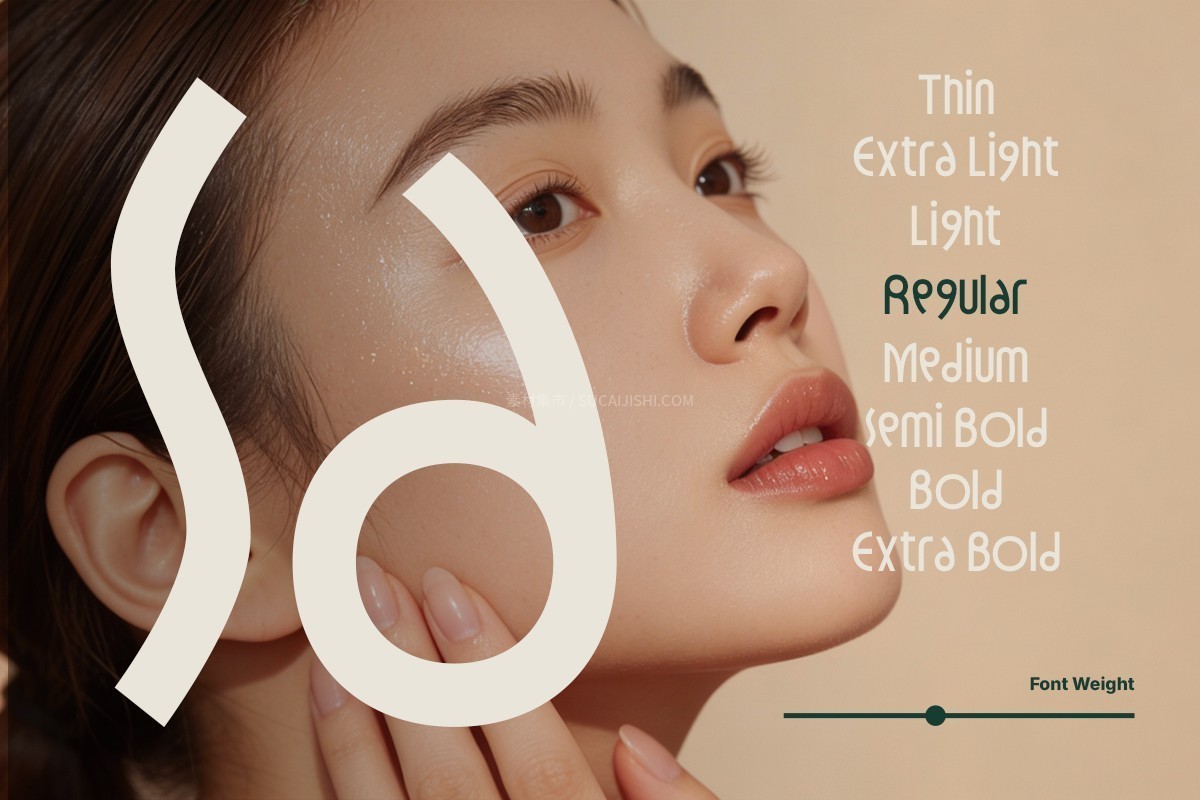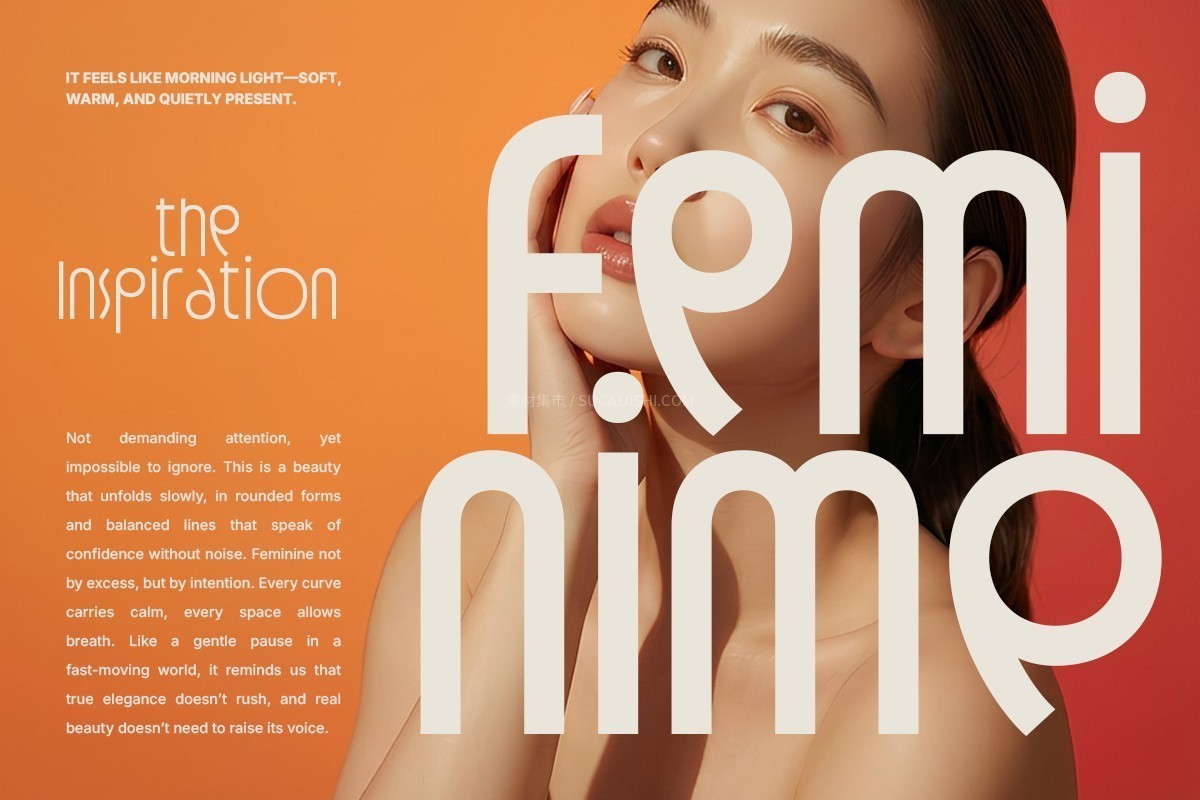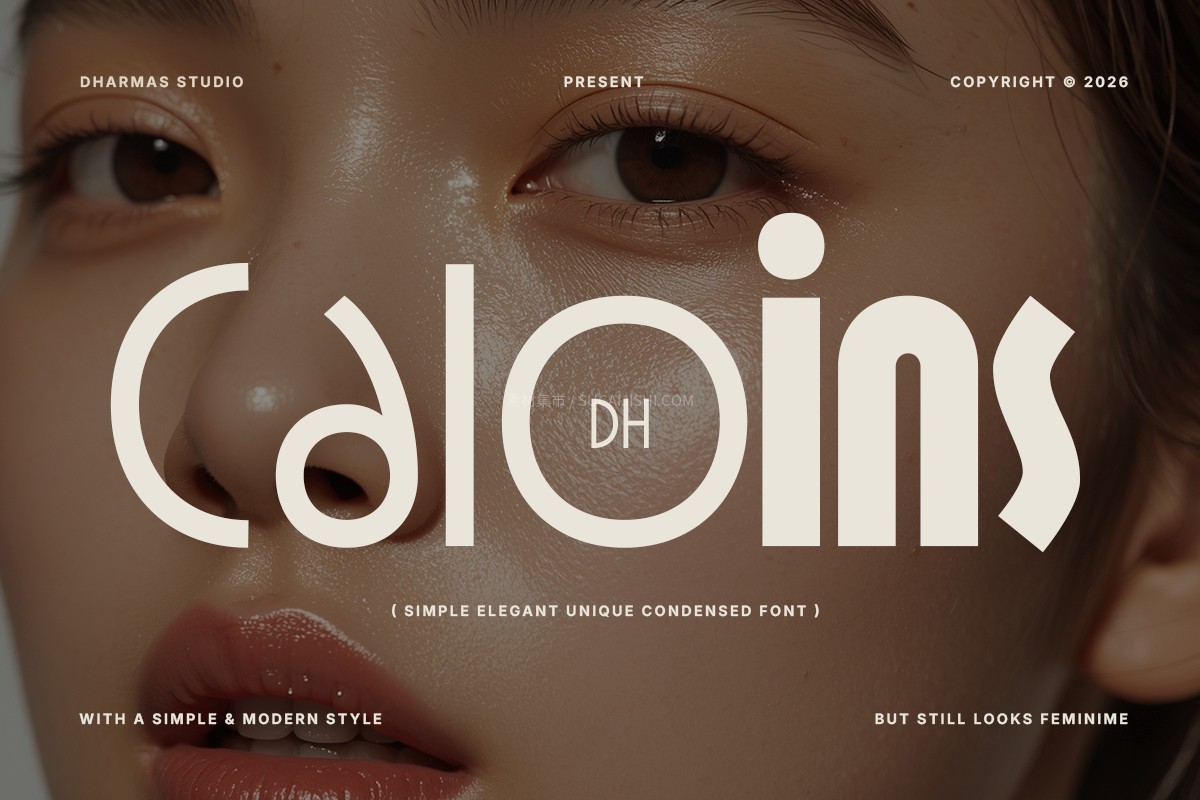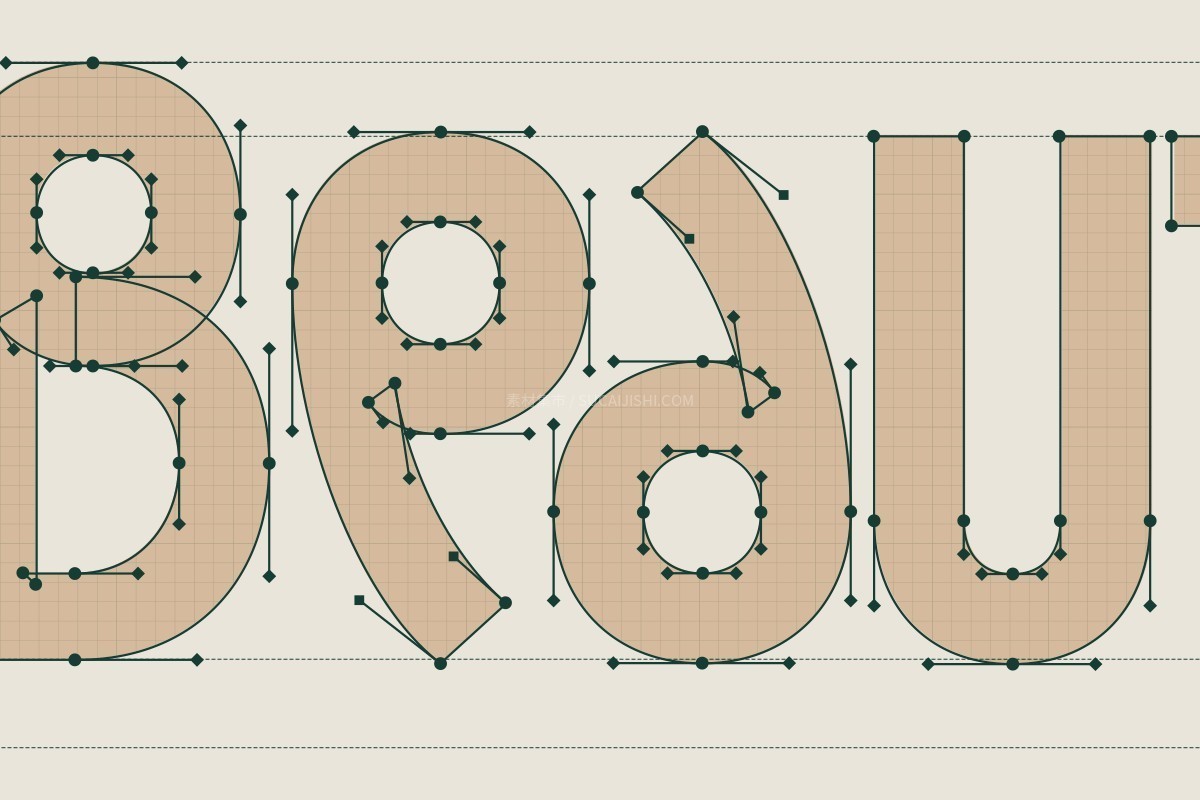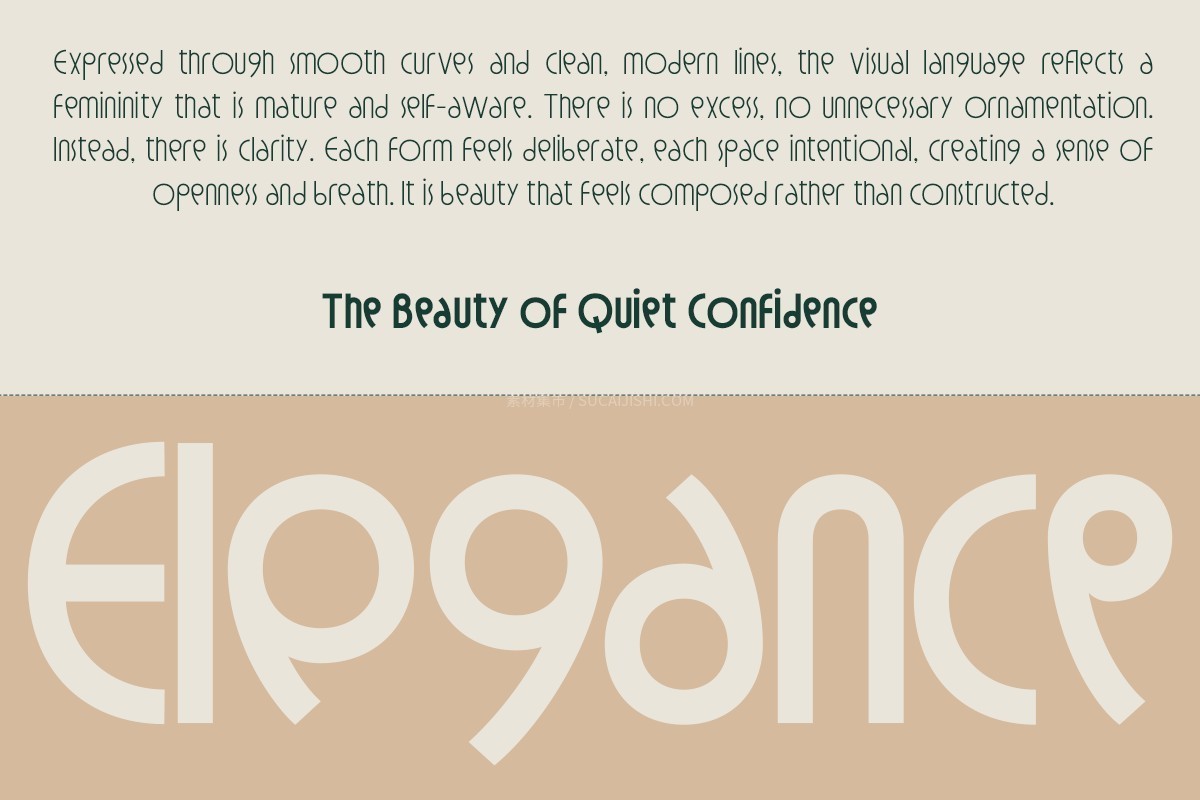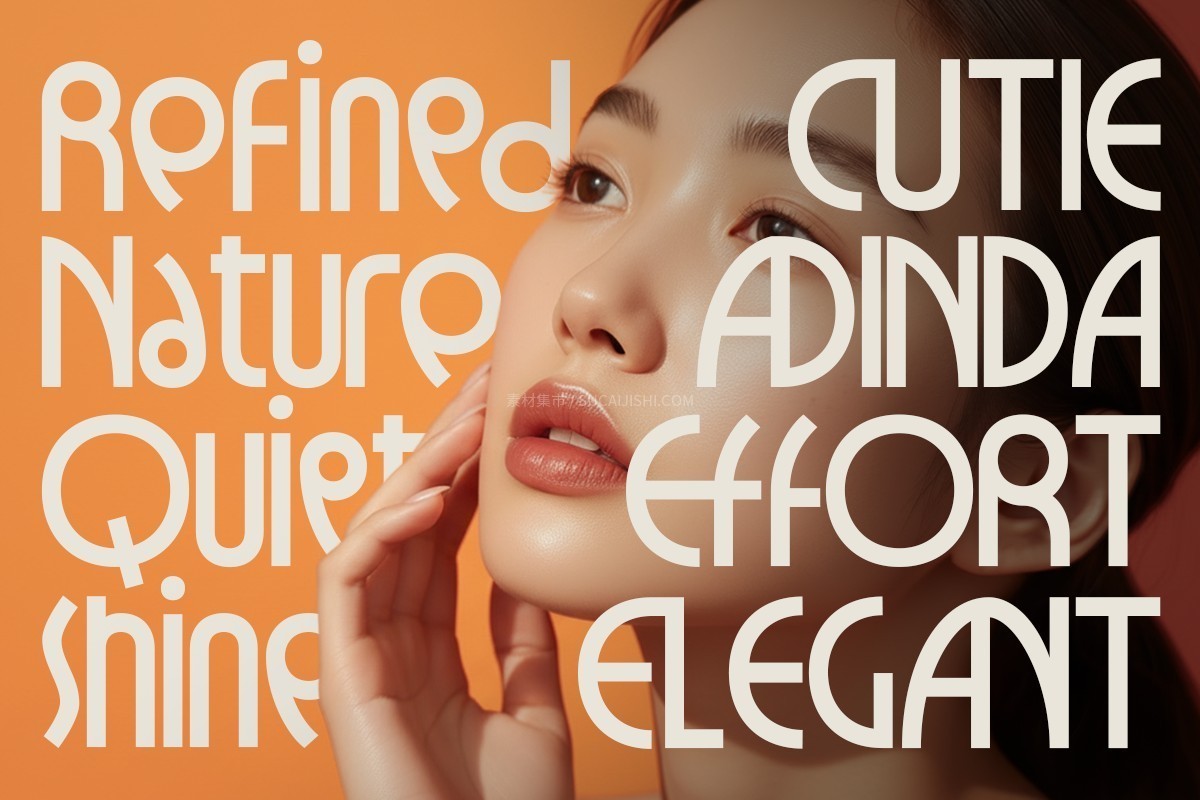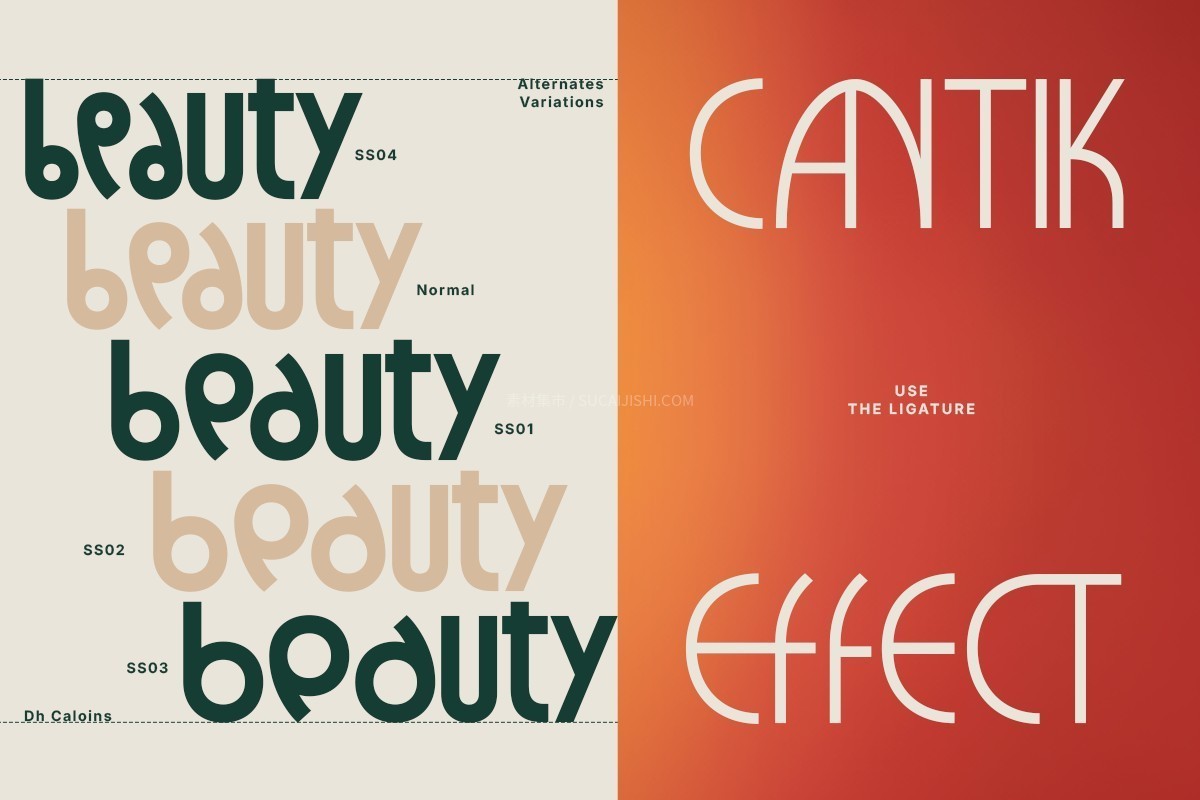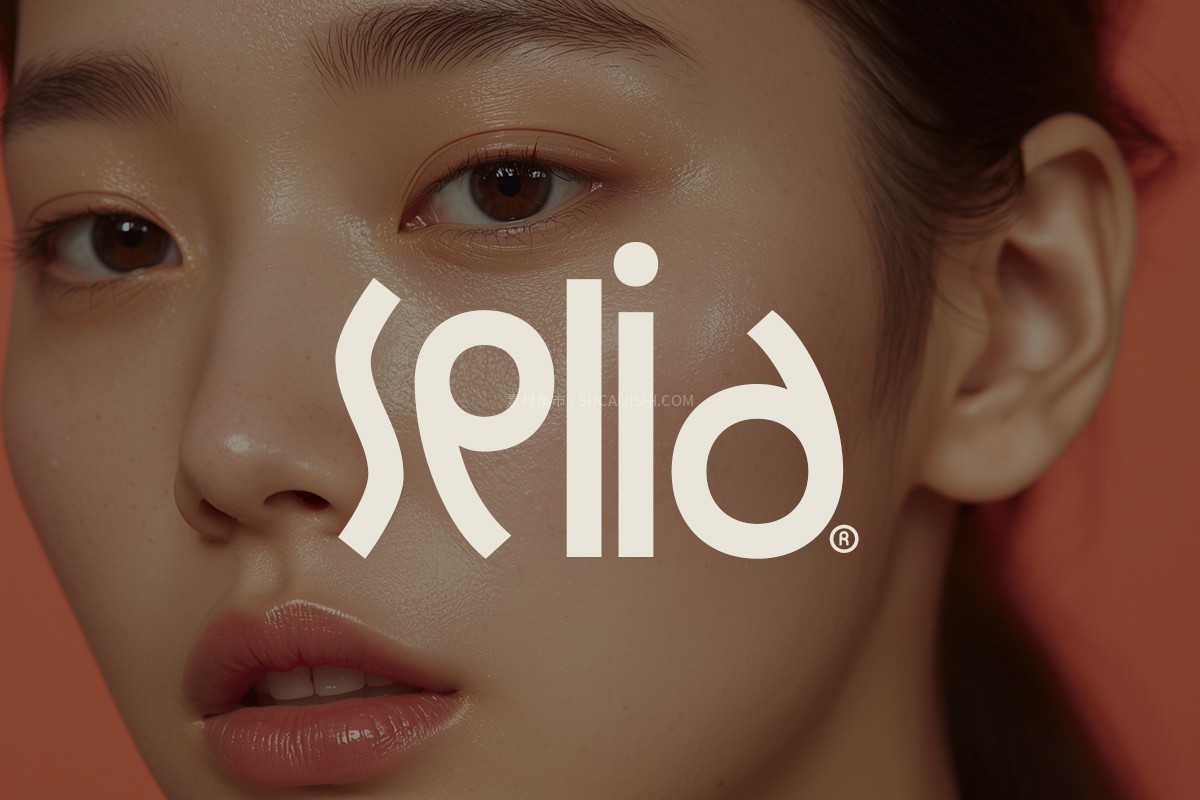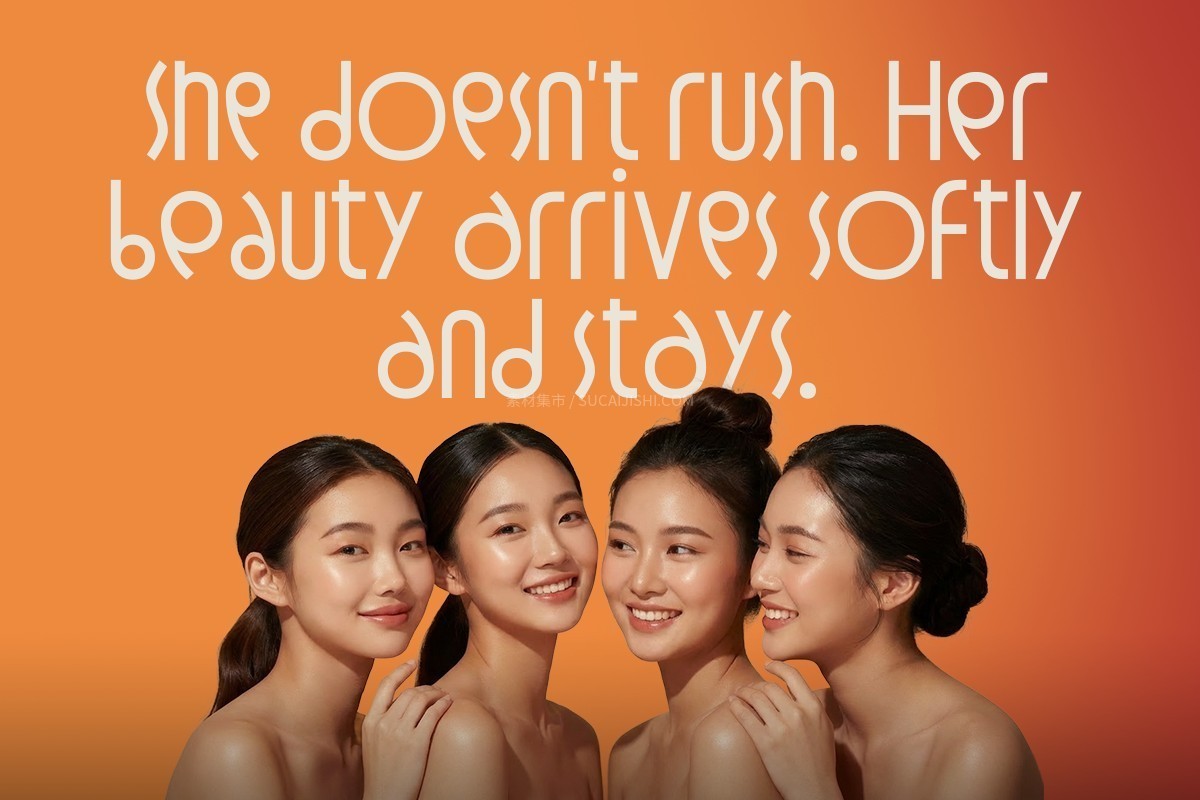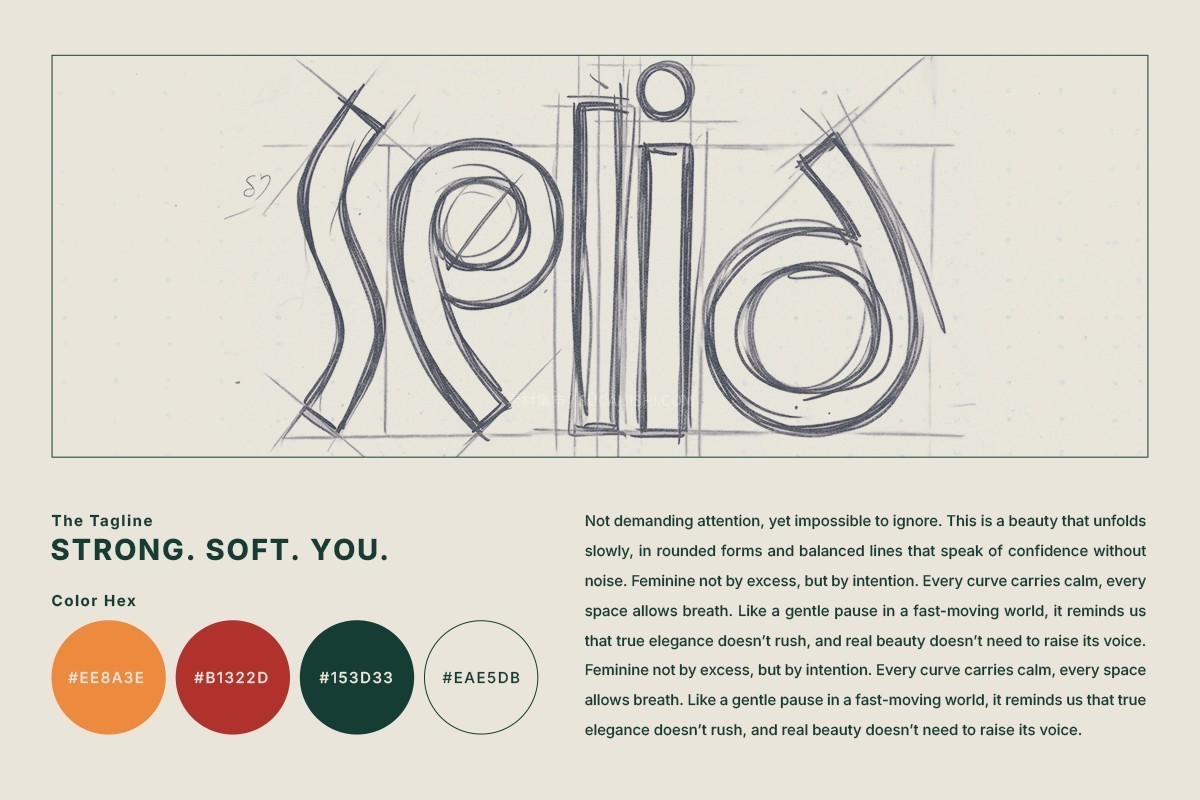
Dh Caloins 高端优雅可变英文字体家族
Dh Caloins 是一款兼具现代美感与艺术表现力的字体家族,专为寻求精致视觉格调的高端设计项目而打造。该家族包含 8 款静态字重(从纤细体 Thin 至特粗体 Extra Bold)及 1 款可变字体(Variable),共计 9 款字体资源。其设计理念融合了流畅的曲线与独特的字形结构,旨在提升美妆、时尚、奢侈品及现代广告等领域的视觉传达质量。该家族凭借灵活的字重分配与高级排版功能,可确保在标题与正文应用中的一致性与可读性。
内置超过 55 种替换字形与连字,支持 PUA 编码,确保在主流设计软件中无需复杂操作即可调用高级排版元素。
多语言字符支持
该字体家族支持广泛的拉丁语系字符集,包括但不限于南非荷兰语、阿尔巴尼亚语、德语、意大利语、西班牙语、瑞典语等多种欧洲及国际通用语言,满足国际化项目的设计需求。